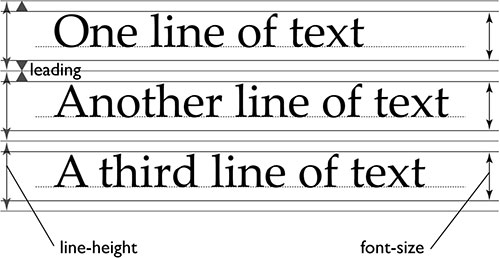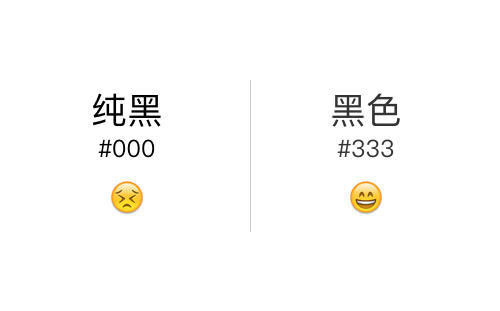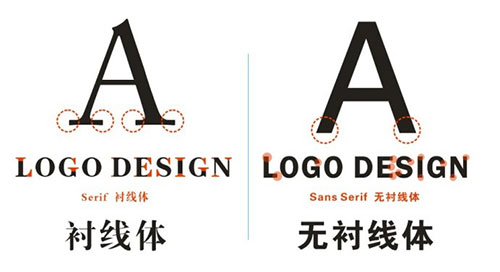
优化阅读体验,网站预设字体的CSS最佳写法
英文字体的文件大小比较小可以使用嵌入字体让网站展示更好,但中文就不一样了,文件大小是 MB 级别,为了 WEB 端性能,只好使用系统自带的默认字体,然而我们有 Windows 和 Mac  OS 两个系统,这两个系统的默认字体是不同的,那么 CSS 中的 font-family、字体大小、颜色、行距如何设置才是最美、最好看的呢?作为网页设计师,对这方面也有所研究,下面是设计达人(公众号ID:shejidaren888)分享下这个设置方法,欢迎一起交流。
注:这里我们只介绍「大多数」的用法,个别特殊设计需求的网站可能不适用此方法。
字体
从用户体验角度来讲,段落文本阅读体验最好的是黑体(无衬线体),而非宋体(衬线体),Win7的时候,字体默认的宋体,而从Windows 10开始,浏览器默认字体改成微软雅黑了,而 Mac OS 默认也是黑体而非宋体。
推荐字体:
Windows:MicroSoft YaHei(微软雅黑)
Mac OS:PingFang SC(苹方)或 Hiragino Sans GB(冬青黑体)
body{
fomt-family: Hiragino Sans GB, MicroSoft YaHei;
}
注:个人喜欢把苹方作为文章标题字体(20PX以上),而冬青黑体作为段落字体。
字体颜色 color
大部网页背景颜色是使用白色,所以字体应该是使用黑色较为友好,当不建议使用纯黑(#000),这是因为纯白底与纯黑的对比太过于强烈,可以使用灰一点的黑色,比如#333,这样能减轻用户视觉负担。
推荐字体颜色:#333
body{
color:#333;
}
字体 font-size
由于现在的电脑屏都是宽屏,手机的屏幕更是高清屏,所以字体大小建议采用16PX字号会比较适合阅读。
推荐字体szie:16px
body{
font-size:16px;
}
字体行距 line-height
字体行距对于阅读也有有很大的影响,比较选中太小,对于多行文字的时候,容易在阅读时「串行」,所以字体的选中个人建议是字体的1.5 – 2.0倍之间。
推荐行距:1.75EM
body{
line-height:1.75;
}
这里后面我没有加入 em,是因为CSS默认就是 em 为单位,所以 em 可以省略不写
最佳 CSS 写法
body {
/*  字体  */
font-family: -apple-system, BlinkMacSystemFont, 'Microsoft YaHei', sans-serif;
/*  字号 */
font-size: 16px;
/*  字体颜色  */
color: #333;
/* 行距 */
line-height: 1.75;
}
这里说明一下-apple-system 和 BlinkMacSystemFont 就是让 MAC OS 自动选择系统字体的意思。
最后,网页设计趋势是不断变化的,比如微软和苹果突然又冒出了一款超牛 X 网页字体……,此时设计师们就要根据需求而变了。